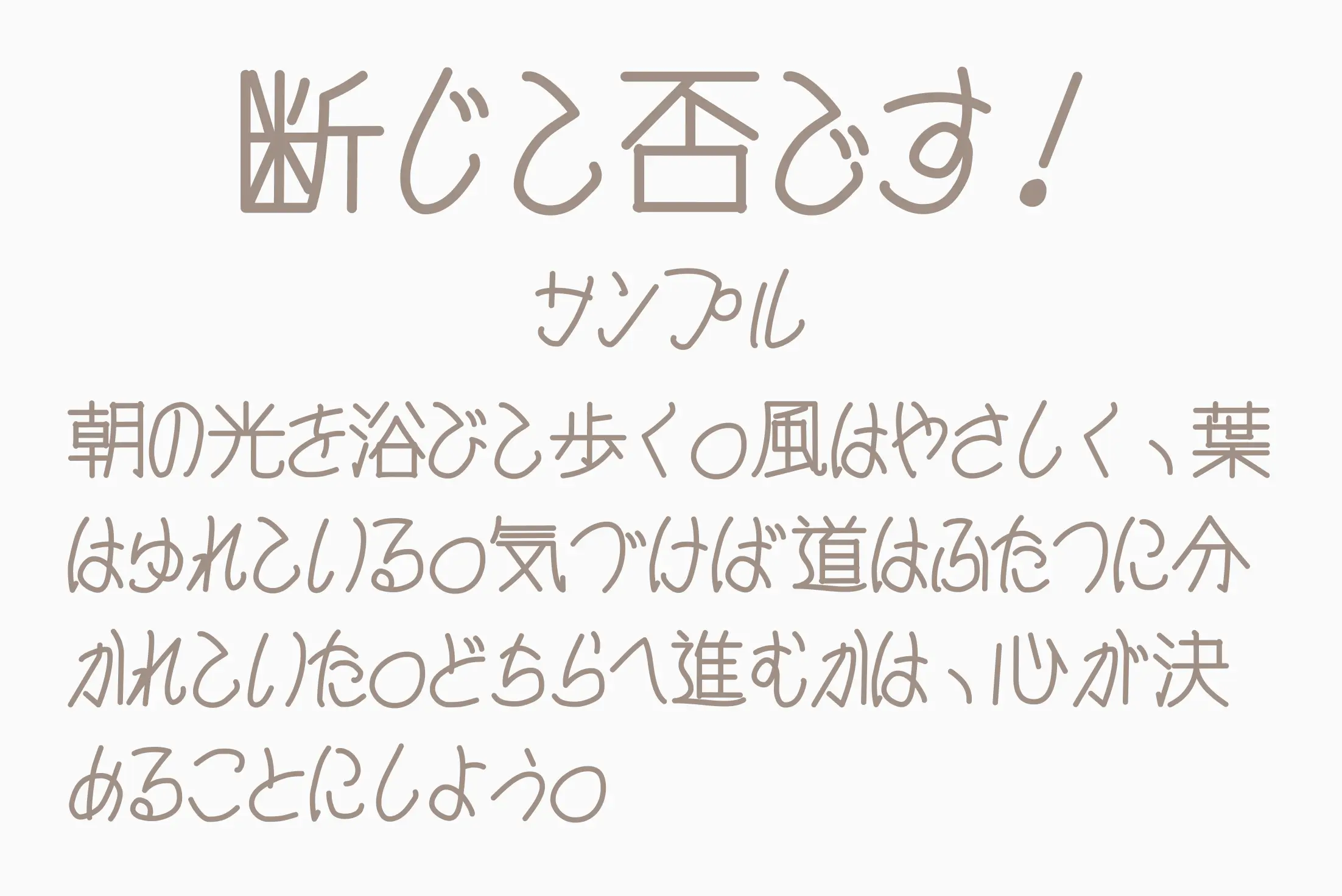
ふにゃっとした揺らぎを残した手書きの風合いが強い個性となっており、均一ではない線の動きが独特のニュアンスを生み出します。整った書体では出せない違和感や雰囲気を表現でき、短い言葉でも印象的に仕上がるのが魅力です。タイトルや一言のフレーズに使うと存在感が際立ち、作品に個性的なアクセントを加えられます。
断じて否です!